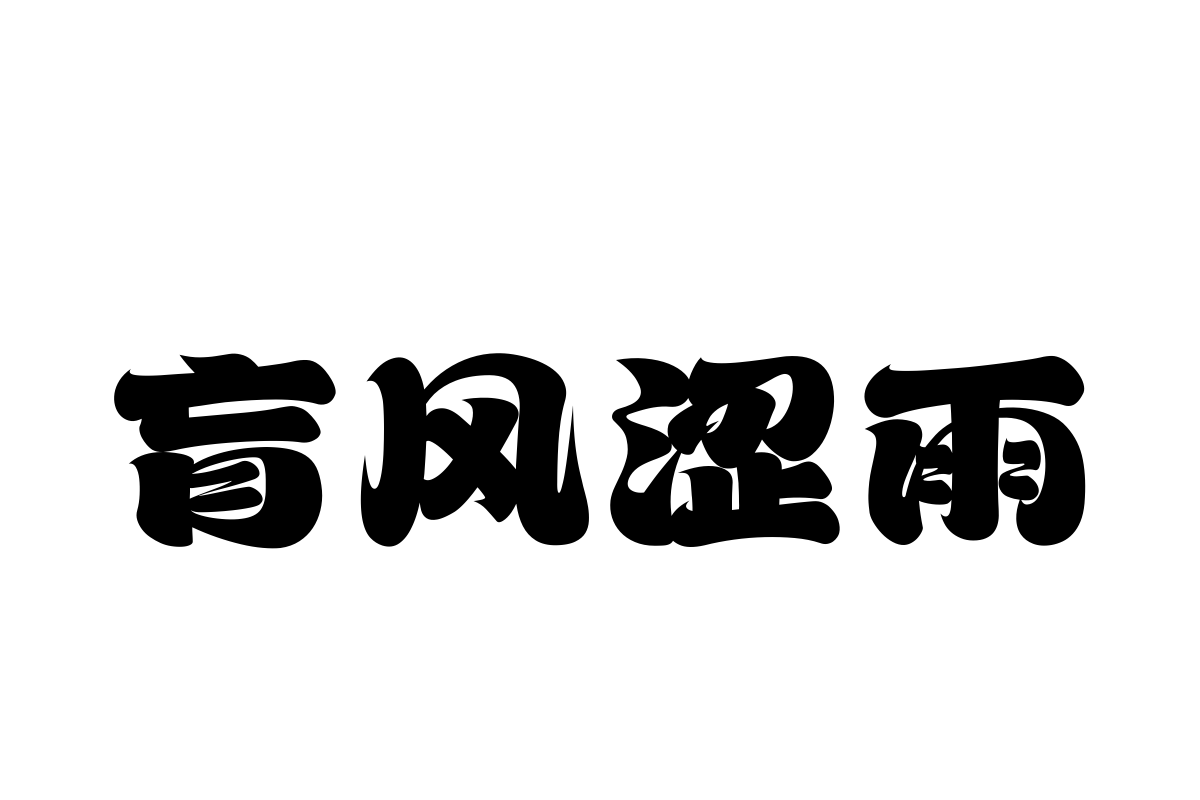
汉仪永字舞狮字体是一款具有浓厚中国传统特色的字体,其特点是字形圆润、饱满,线条流畅,富有动感。这款字体适用于各种中文文本的排版设计,如书籍封面、杂志、海报、广告等。
永字舞狮字体的特点如下:
1. 字形圆润饱满:字体的笔画圆润饱满,给人一种温馨、亲切的感觉,适合用于表现喜庆、吉祥的氛围。
2. 线条流畅:字体的笔画流畅自然,没有生硬的断点和突兀的起笔,使整个字体看起来更加和谐、美观。
3. 富有动感:字体的笔画起伏有致,具有较强的动态感,能够很好地传达出舞狮表演时的欢快、热烈气氛。
4. 适用范围广泛:永字舞狮字体适用于各种中文文本的排版设计,无论是标题、正文还是注释,都能展现出独特的韵味和风格。
5. 兼容性强:汉仪永字舞狮字体支持多种字体设置,如大小、粗细、行距等,可以根据实际需求进行调整,以达到最佳的视觉效果。
总之,汉仪永字舞狮字体是一款具有浓厚中国传统文化特色的字体,适用于各种中文文本的排版设计,能够很好地传达出喜庆、吉祥的氛围。